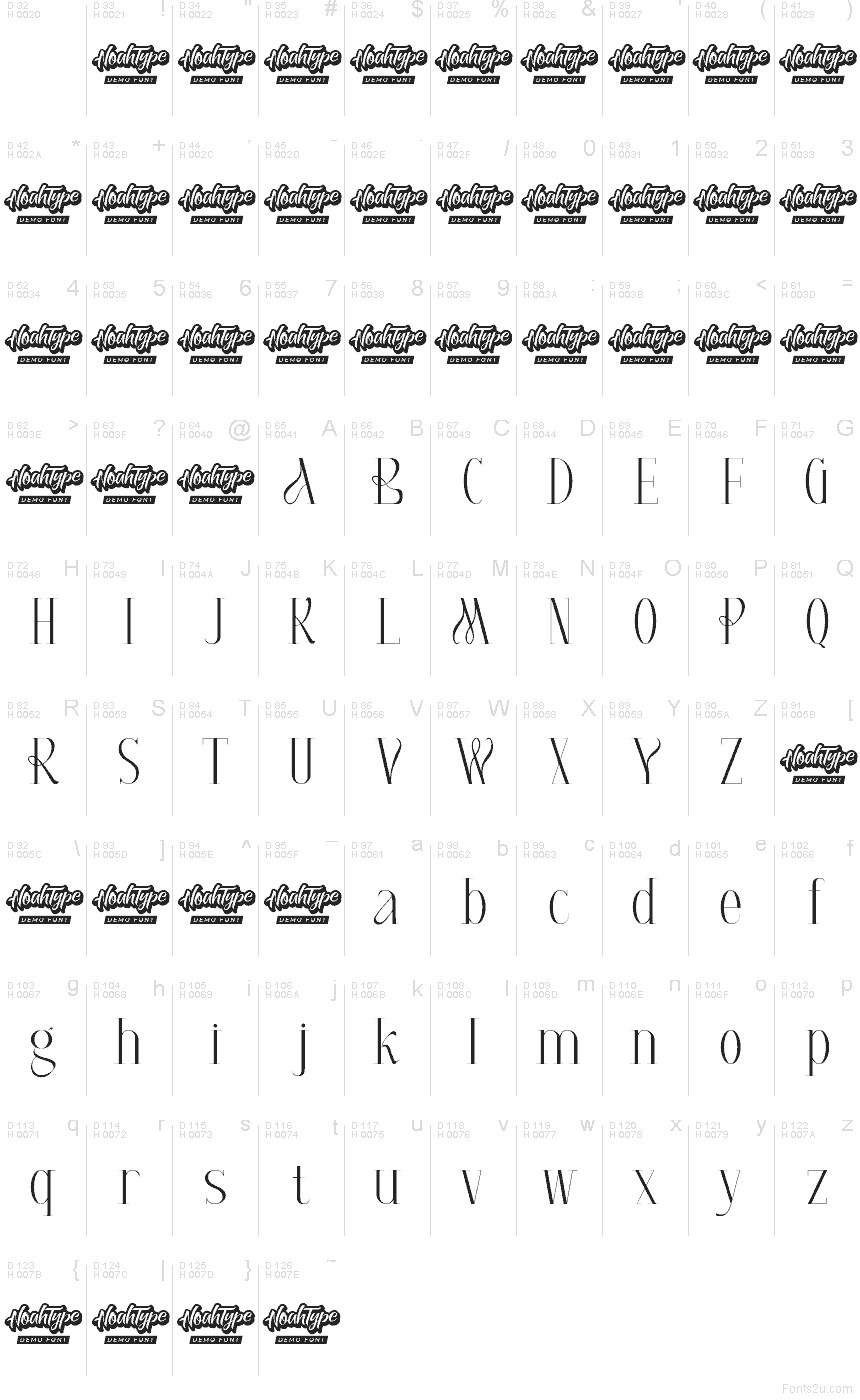
Star Paradise od NoahType je bezplatné, vysoce kontrastní titulkové písmo definované svou velmi vysokou, vzdušnou siluetou a rozmáchlými křivkami, díky kterým jsou písmena elegantní a nikoli tuhá. Dlouhé svislé linie a jemné spoje vytvářejí vytříbený rytmus, zatímco příležitostné smyčky dodávají designu lehce dramatický nádech.
Tato kombinace dává smysl v módních editorialech, na obalech parfémů, v logách butiků, na pozvánkách na akce a u velkých titulků, kde vynikne štíhlá a protáhlá podoba písma. Skvěle se hodí také pro beauty branding a záhlaví na sociálních sítích, zejména pokud hledáte písmo, které působí půvabně a dekorativně, aniž by bylo příliš zdobné.